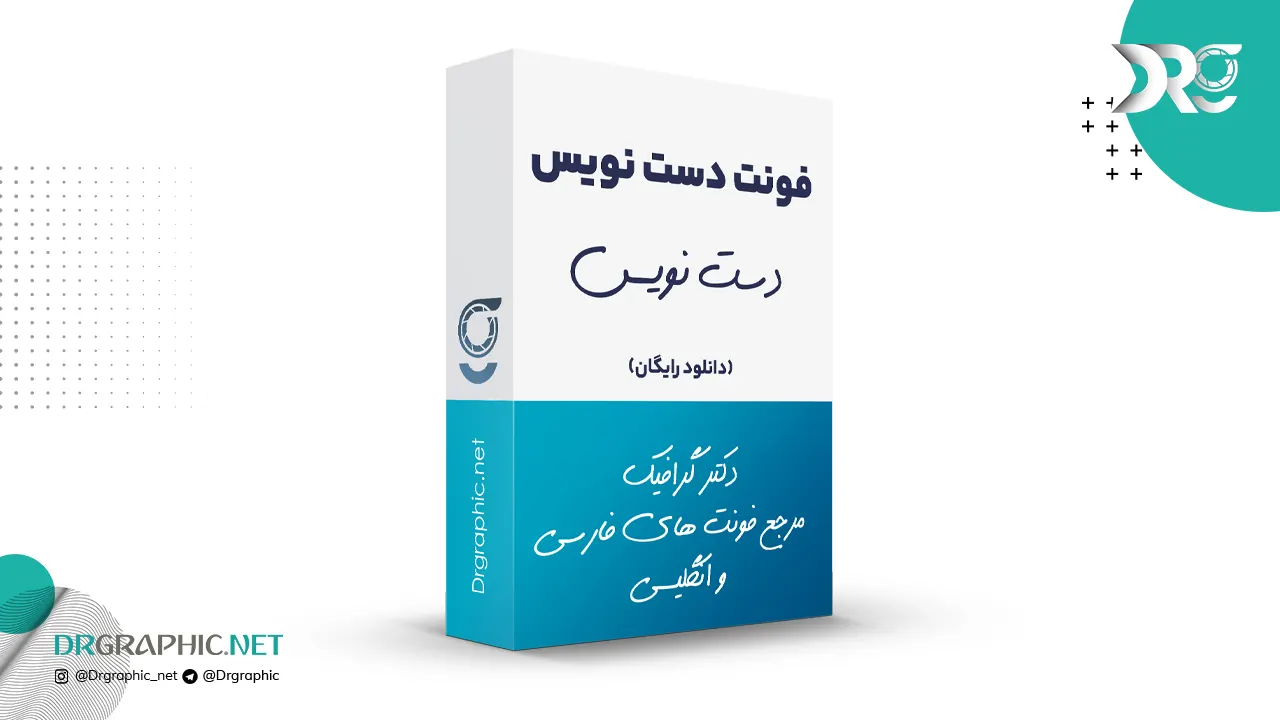
دانلود فونت فارسی دست نویس Dast Nevis
فونت های دست نویس از جمله فونت هایی هستند که زیبایی و تاثیر گذاری بیشتری نسبت به فونت های ساده و استاندارد دارند. این فونت ها با دست نوشته شده اند و معمولاً شامل خطوط زیبا و خاص هستند که به طراحی متن شما جذابیت و جلوه ای خاص می بخشند. با دکتر گرافیک همراه باشید.
استفاده از فونت های دستنویس در طراحی وب سایت، طرح های گرافیکی، بروشورها، کارت ویزیت ها و … به دلیل ظاهر جذاب و خاص این فونت ها، از محبوبیت بالایی برخوردار است.